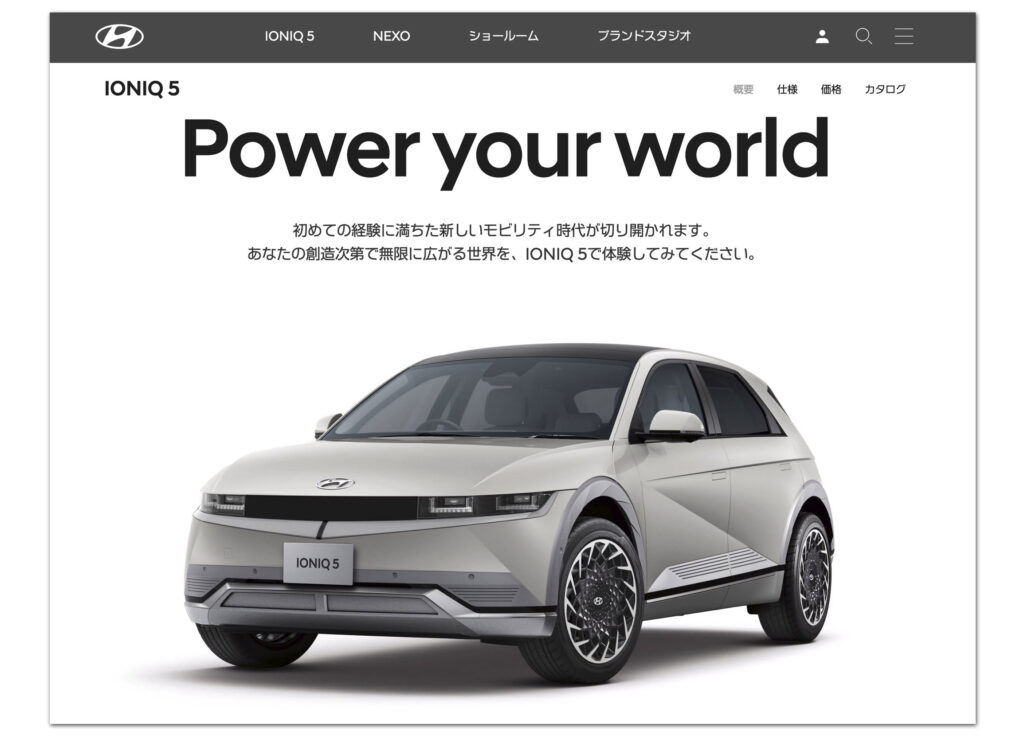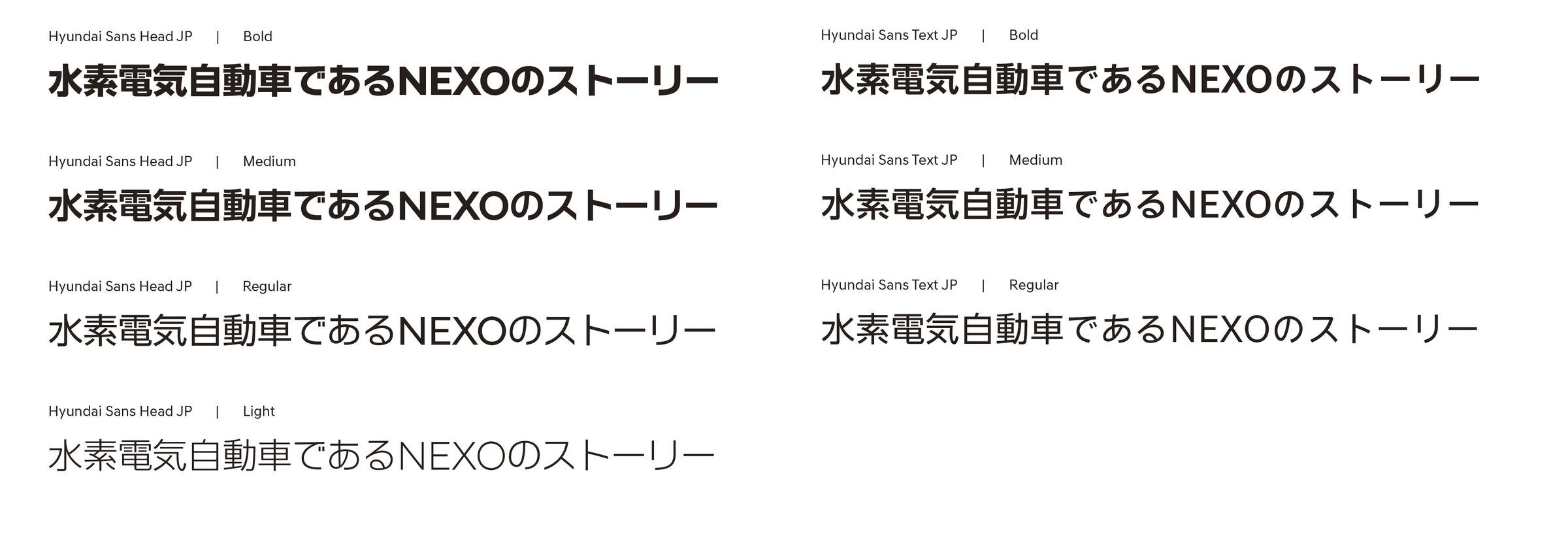
モリサワ Hyundai Motor Companyの日本語コーポレートフォントをモリサワが開発
株式会社モリサワは、 日本の乗用車市場に再参入した韓国・Hyundai Motor Company(ヒョンデ モーター カンパニー)のコーポレートフォント「Hyundai Sans」の日本語フォント「Hyundai Sans JP」を開発・提供した。
Hyundai Motor Companyは、日本の乗用車市場への再参入に伴い、日本法人名を「Hyundai Mobility Japan(ヒョンデ モビリティ ジャパン)」とし法人名を変更。ハングル、欧文など進出市場で使用しているコーポレートフォントに日本語を追加することとし、モリサワと共同開発した。同コーポレートフォント「Hyundai Sans JP」は、日本販売されているゼロ・エミッション・ビークル(ZEV)である「IONIQ 5(アイオニック 5)」(BEV:バッテリー式電気自動車)と「NEXO(ネッソ)」(FCEV: 水素電気自動車)の広告や、ヒョンデ モビリティ ジャパン公式サイトなどで利用され、今後日本での活動において利用範囲を広げていくとしている。
今回採用された「Hyundai Sans Head JP」「Hyundai Sans Text JP」は、それぞれタイトルと本文での利用などを想定している。
欧文コーポレートフォント「Hyundai Sans Head」との一貫性を重視し、ジオメトリック、スムーズ、モビリティをコンセプトキーワードとして作成した「Hyundai Sans Head JP」に対し、本文利用の「Hyundai Sans Text JP」はレスジオメトリックで、より自然で馴染みのあるゴシック体となっている。
「Hyundaiのグローバルで統一したブランドイメージを新しい日本市場でも踏襲していく必要があり、 Hyundai Sansに合わせて日本語のコーポレートフォントを策定しました。 オンラインでの販売のため、 文字への依存が高く、 フォントの役割は重要です。 シンプルで読みやすく、 消費者の皆さまに評価いただいています。 」
「グローバルブランドであるHyundaiの日本市場参入をサポートすることができて大変光栄です。 今回は、 弊社の韓国現地法人が窓口となって完遂することができました。 日本企業の海外展開や、 海外企業の日本またはアジア展開に伴い、 日本語フォントや欧文フォント、 中国語・韓国語フォントなどをお手伝いするケースも増えており、 グローバルネットワークを活かし対応していきます。 」